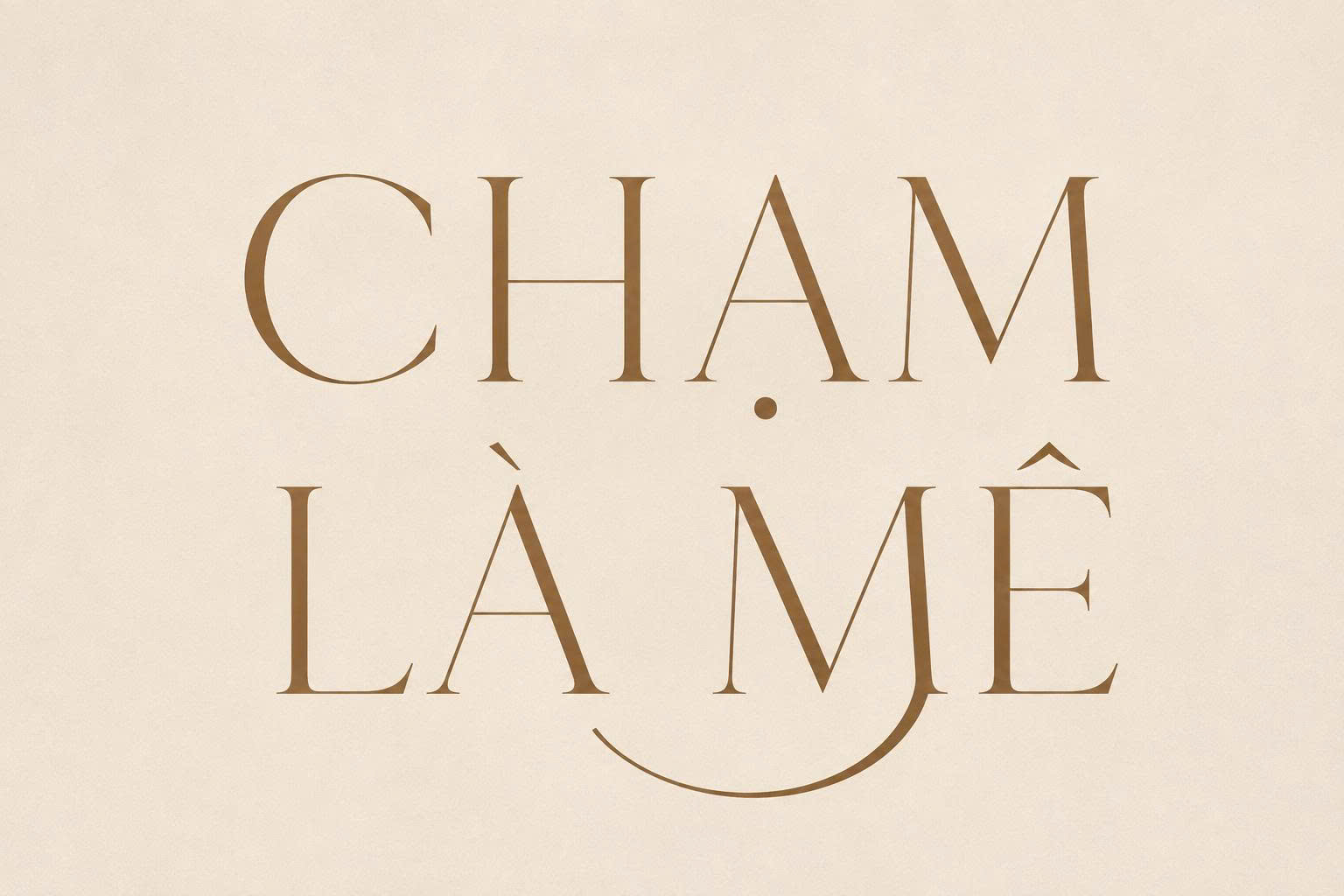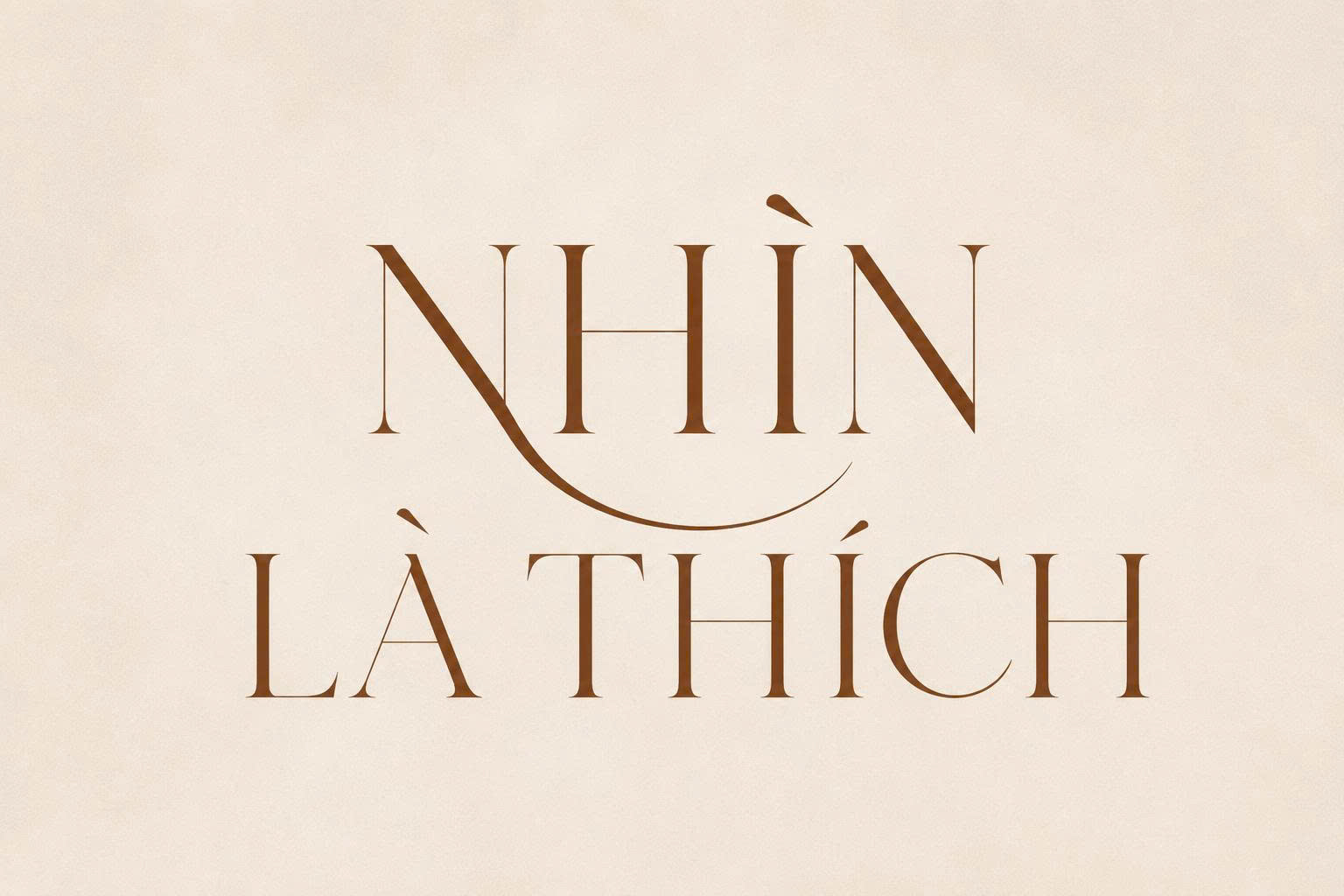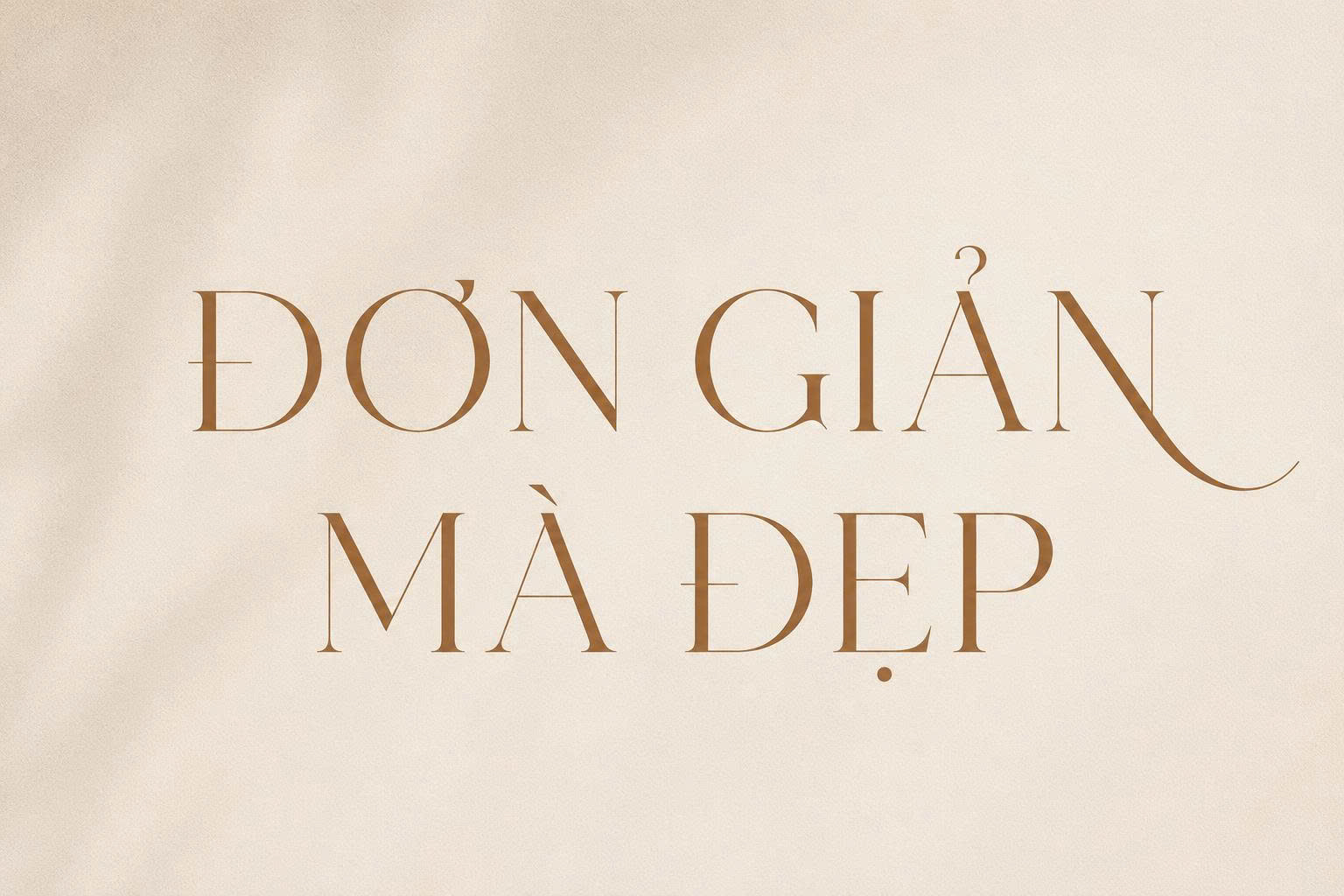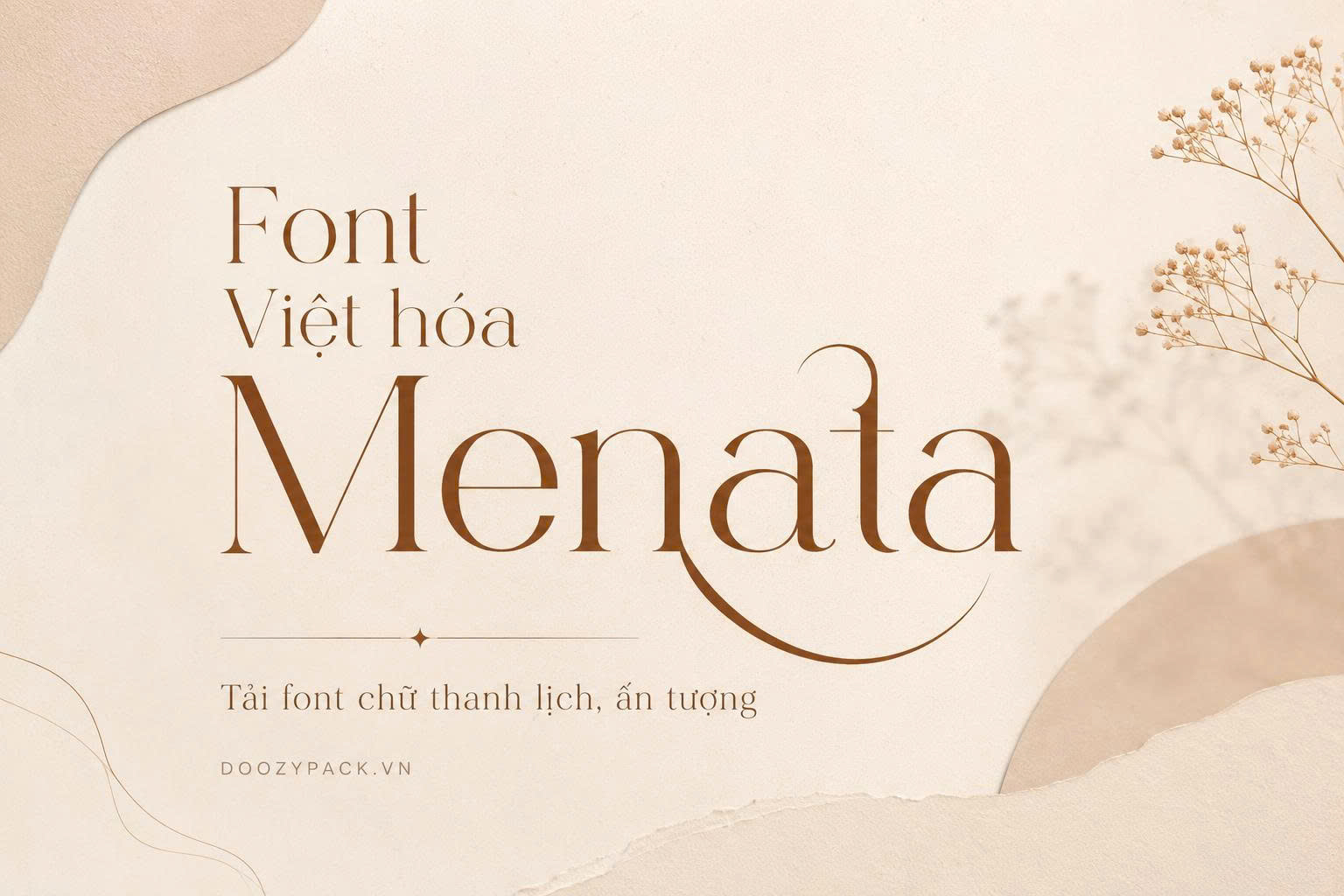
Font Việt hóa Menata là bộ phông chữ có chân (Serif) mang phong cách hiện đại, thanh lịch và vô cùng thời thượng. Với cấu trúc chữ tinh tế, những đường cong uốn lượn mềm mại kết hợp cùng các nét thẳng sắc sảo, Menata đã trở thành lựa chọn hàng đầu cho các dự án thiết kế logo, bao bì mỹ phẩm và nhận diện thương hiệu cao cấp. Doozypack.vn chia sẻ link tải font Menata Việt hóa chuẩn, giúp bạn sở hữu bộ font Menata tiếng Việt hoàn chỉnh, không lỗi dấu thanh để nâng tầm đẳng cấp cho mọi bản thiết kế.
Đặc điểm thiết kế tinh tế của bộ font Menata Việt hóa
Menata không chỉ là một phông chữ Serif thông thường; nó là sự kết hợp giữa nét cổ điển quý phái và ngôn ngữ đồ họa đương đại, mang lại diện mạo vô cùng lôi cuốn.
Vẻ đẹp thanh lịch với những đường cong nghệ thuật
Đặc trưng lớn nhất của font Việt hóa Menata là sự tương phản nhẹ nhàng giữa các nét thanh và nét đậm. Điểm nhấn nằm ở các chi tiết uốn lượn tại các ký tự như ‘a’, ‘g’, ‘y’, tạo nên một nhịp điệu Typography vô cùng nữ tính và sang trọng. Cấu trúc chữ của Menata gợi nhắc đến những nhãn hàng Luxury toàn cầu, tạo cảm giác về sự sang trọng và uy tín ngay từ cái nhìn đầu tiên.
Hệ thống dấu tiếng Việt được xử lý chỉn chu
Nhiều bộ font Serif hiện đại thường gặp vấn đề khi hiển thị tiếng Việt như dấu thanh bị đè nét hoặc sai lệch vị trí. Phiên bản font Menata tiếng Việt tại Doozypack.vn đã được tối ưu hoàn toàn. Các bộ dấu sắc, huyền, hỏi, ngã, nặng được thiết kế thanh mảnh đồng nhất với thân chữ, đảm bảo văn bản luôn giữ được sự thanh thoát và chuyên nghiệp tuyệt đối ngay cả khi trình bày ở kích thước nhỏ.
Tại sao designer nên chọn font Menata cho thiết kế bao bì?
- Nâng tầm giá trị sản phẩm: Menata mang lại diện mạo “Premium” ngay tức thì, đặc biệt hiệu quả khi ứng dụng cho ngành mỹ phẩm, nước hoa và thời trang cao cấp.
- Tạo dấu ấn thương hiệu độc bản: Phong cách Serif hiện đại của Menata giúp bao bì sản phẩm của bạn nổi bật hoàn toàn so với các đối thủ sử dụng phông chữ không chân thông thường.
- Phân cấp thông tin linh hoạt: Menata hoạt động tốt cả khi làm tiêu đề chính lẫn các đoạn văn bản ngắn, giúp bản thiết kế đạt được sự đồng bộ về mặt thẩm mỹ.
- Thiệp mời & Menu Spa: Nét chữ Serif thanh thoát của Menata là lựa chọn tuyệt vời cho các dịch vụ chăm sóc sắc đẹp và thiệp mời sự kiện trang trọng.